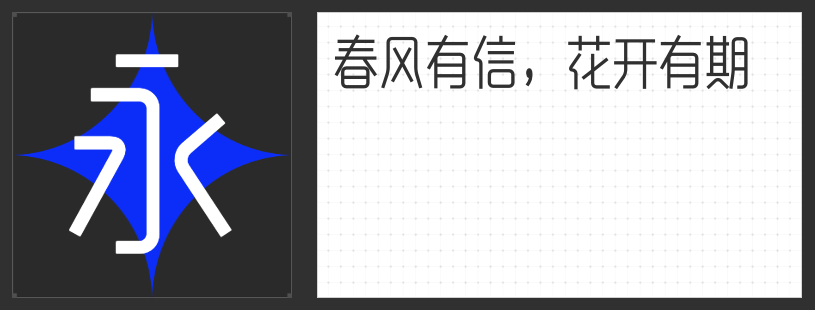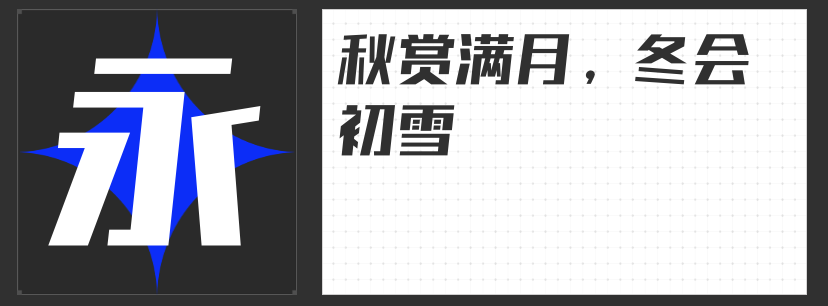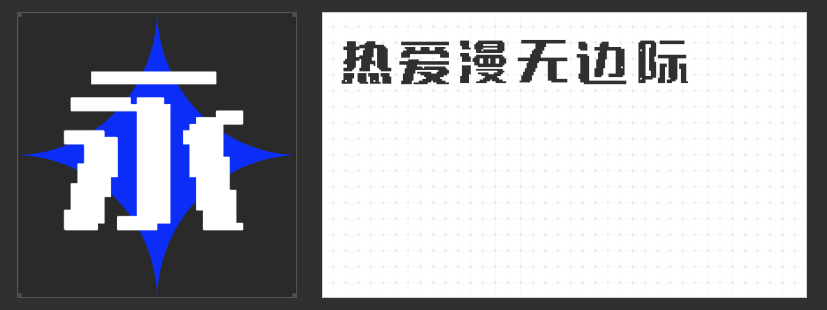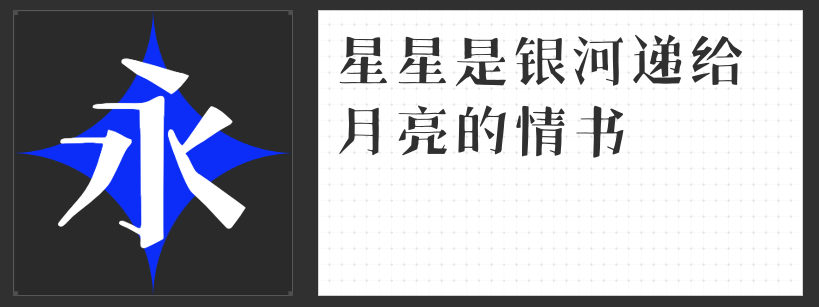
高手庆科字体:创意与经典的完美融合
在探索字体的奇妙世界里,高手庆科字体无疑是一座宝藏库,它汇聚了四款独具魅力的字体,每一款都蕴含着设计师的匠心独运与无限创意。接下来,让我们一起领略这几款字体的独特魅力。
第一款:高手庆科静雅体 瘦版
高手庆科静雅体 瘦版,以其温婉而不失力度的笔触,营造出一种宁静致远的氛围。这款字体在保留传统韵味的同时,融入了现代审美,使得它在书籍装帧、海报设计等领域都能大放异彩。无论是想要传达古典美还是追求简约风格,高手庆科静雅体 瘦版都能完美胜任,让人在字里行间感受到一份淡然与从容。
第二款:高手庆科帅黑体 大黑
高手庆科帅黑体 大黑,以其独特的粗犷线条和强烈的视觉冲击力,成为了现代设计中不可或缺的一员。高手庆科帅黑体 大黑适用于需要展现力量感、科技感或时尚感的场景,如电子产品宣传、运动品牌标识等。高手庆科帅黑体 大黑的每一个字都仿佛充满了力量,让人一眼难忘,是追求个性与独特性的设计师们的首选。
第三款:高手庆科手绘宋
高手庆科手绘宋,将传统宋体的韵味与现代手绘的灵动完美结合,创造出一种独特的艺术效果。这款字体仿佛是用画笔一笔一划勾勒而成,充满了人情味和艺术感。高手庆科手绘宋适用于文艺创作、手账记录等场景,能够瞬间提升作品的格调与温度,让人感受到文字的温暖与力量。
第四款:高手庆科数码体 大黑
高手庆科数码体 大黑,以其简洁明快的线条和清晰的辨识度,成为了数字时代下的宠儿。高手庆科数码体 大黑适用于各种屏幕显示场景,如网页设计、APP界面等,能够确保文字在不同设备上都能保持良好的阅读体验。高手庆科数码体 大黑的设计充分考虑了现代人的阅读习惯和信息获取方式,使得文字与信息更加高效地传达给受众。
总之,这四款字体各具特色,无论是追求传统韵味还是现代时尚感,都能在这里找到心仪的选择。它们不仅是设计师手中的得力工具,更是传递情感、表达创意的重要载体。